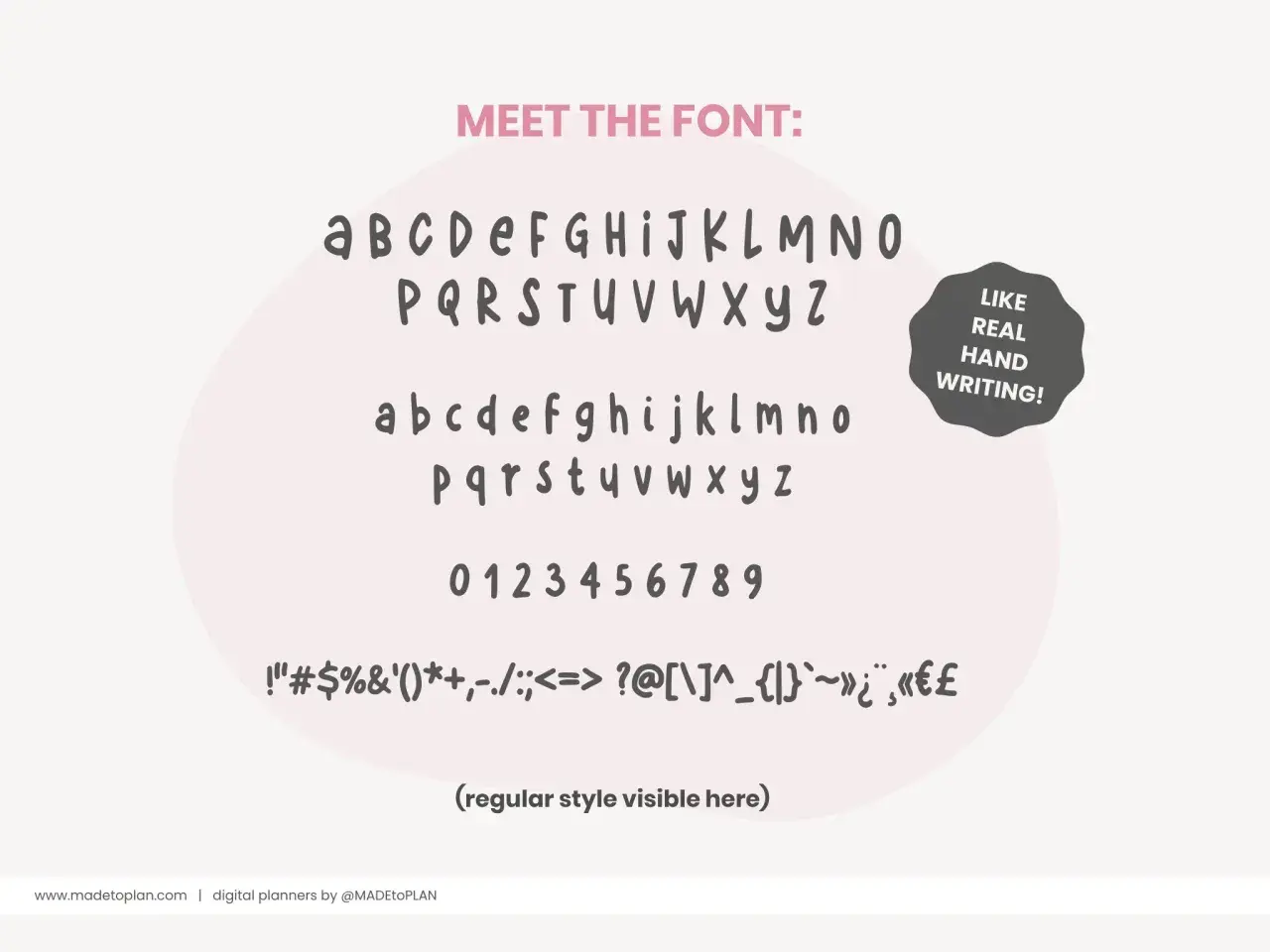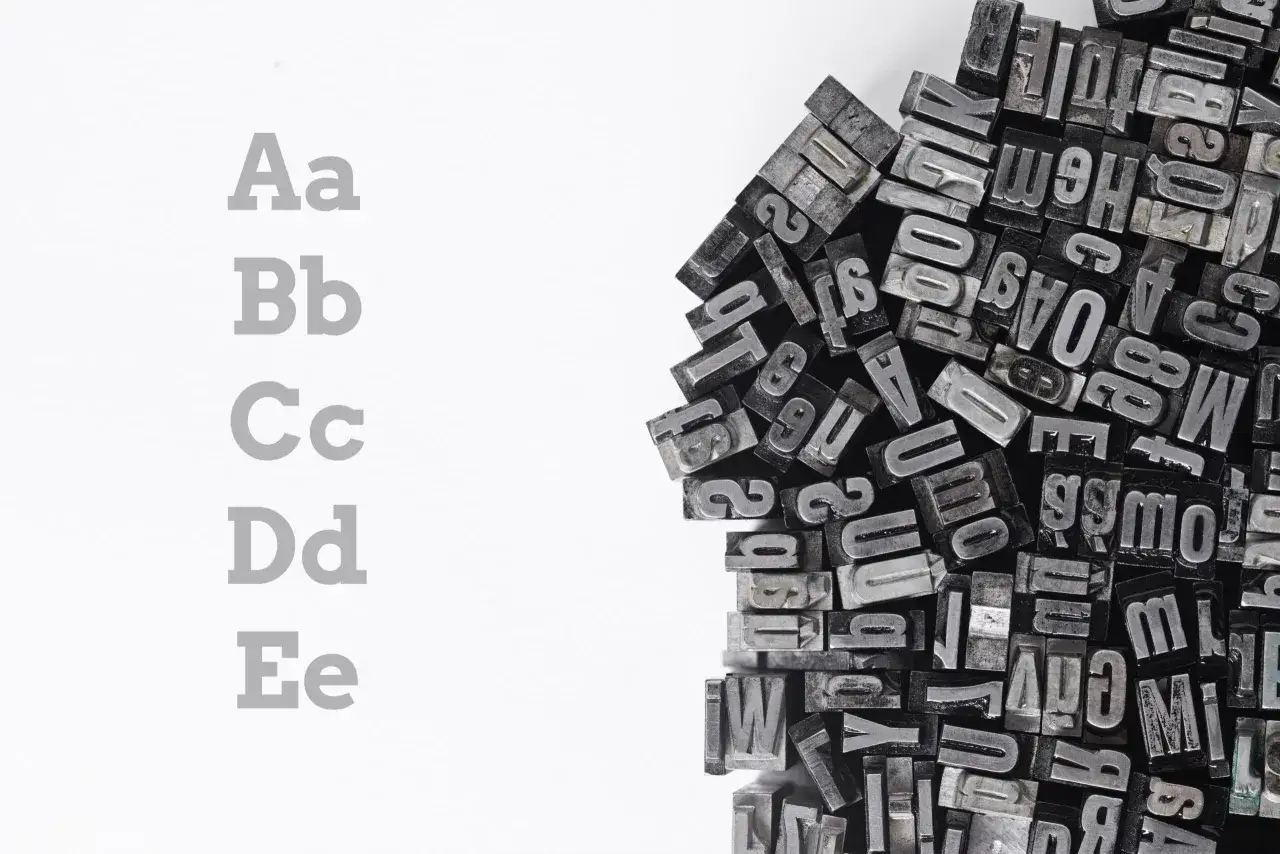
Czcionka, font, krój pisma - Wybierz idealny dla Twojej strony!
Przedstawienie czcionki co to jest, z literami, cyframi i symbolami. Wygląda jak prawdziwe pismo ręczne.
Czcionka to jeden z tych terminów, które brzmią prosto, a w praktyce potrafią mieszać się z fontem i krojem pisma. Poniżej rozkładam to na części: od znaczenia w typografii, przez różnice pojęciowe, aż po to, jak dobrać czytelny zestaw liter na stronie internetowej lub w sklepie online. Dzięki temu łatwiej uniknąć nieporozumień i wybrać rozwiązanie, które dobrze wygląda, szybko się ładuje i nie męczy wzroku.
Najważniejsze rzeczy o czcionkach w skrócie
• Czcionka historycznie oznaczała fizyczny nośnik pojedynczego znaku, a dziś w praktyce często bywa używana zamiennie z fontem.
• W typografii ważniejsze od samej nazwy jest to, czy tekst pozostaje czytelny, spójny i dopasowany do celu strony.
• W internecie font to zwykle plik z zestawem znaków i odmian, który musi ładować się szybko oraz poprawnie obsługiwać polskie znaki.
• Najbezpieczniej wybierać 1-2 rodziny krojów, kilka wag i dbać o odstępy, kontrast oraz wersję mobilną.
• Zły dobór pisma nie tylko psuje estetykę, ale też obniża komfort czytania i skuteczność treści.
Czym jest czcionka w typografii i codziennym użyciu
W klasycznym drukarstwie czcionka była fizycznym elementem używanym do składania tekstu. Jeden znak miał swój materialny odpowiednik, więc litery istniały dosłownie jako metalowe lub drewniane klocki. To właśnie stąd wzięło się pojęcie, które do dziś funkcjonuje w języku potocznym.
W codziennej rozmowie czcionką nazywa się zwykle cały wygląd pisma, czyli to, czy litery są eleganckie, techniczne, nowoczesne albo dekoracyjne. W praktyce projektowej ja patrzę na to szerzej: nie tylko na sam kształt liter, ale też na ich czytelność, odstępy, grubość kresek i zachowanie w różnych rozmiarach. To ważne, bo ten sam zestaw znaków może wyglądać świetnie w nagłówku, a słabo w dłuższym akapicie.
Dlatego przy pracy z tekstem warto pamiętać o prostym rozróżnieniu: historyczna czcionka to rzecz z drukarni, a współczesny wybór na ekranie to już przede wszystkim decyzja typograficzna i technologiczna. Żeby nie mieszać pojęć, od razu rozdzielam trzy terminy, które najczęściej wrzuca się do jednego worka.
Metalowe czcionki, co to za litery? Obok nich Aa, Bb, Cc, Dd, Ee.
Różnica między czcionką, fontem i krojem pisma
Tu najczęściej pojawia się nieporozumienie. Jeśli pracuję nad tekstem na stronie, używam tych słów precyzyjnie, bo każde z nich opisuje trochę inny poziom:
Pojęcie Co oznacza Przykład Kiedy ma sens
Czcionka Historycznie fizyczny nośnik pojedynczego znaku używany w druku Metalowa litera w składzie drukarskim Gdy mówimy o klasycznej poligrafii i historii pisma
Krój pisma Projekt liter i znaków o wspólnych cechach graficznych Times New Roman, Inter, Georgia Gdy opisujemy wygląd i styl pisma
Font Cyfrowa postać kroju pisma, zwykle w konkretnej wadze i odmianie Inter Regular, Inter Bold, Inter Italic Gdy mówimy o pliku lub wersji użytej w systemie
Glif Konkretny rysunek znaku w danym kroju Wersja litery „a” w danym foncie Gdy analizujemy szczegóły kształtu liter i symboli
W praktyce potoczne użycie bywa uproszczone i mało kto w rozmowie codziennej pilnuje tej granicy co do przecinka. W pracy nad stroną, identyfikacją wizualną albo materiałami sprzedażowymi takie rozróżnienie pomaga jednak uniknąć chaosu: łatwiej wtedy dobrać wariant, rozmiar, wagę i zestaw znaków, który faktycznie działa. Gdy to już jasne, można przejść do tego, jak font funkcjonuje w świecie cyfrowym.
Jak font działa w internecie i na urządzeniu
W informatyce font to najczęściej plik z opisem znaków, ich kształtów i odmian. Współczesne fonty są zwykle wektorowe, więc skalują się bez utraty ostrości, a nie jako proste bitmapy. To dlatego ten sam krój może dobrze wyglądać na małym ekranie telefonu i na dużym monitorze, o ile został poprawnie przygotowany.
Na stronach internetowych najczęściej spotykam format WOFF2, bo jest lekki i dobrze wspierany przez nowoczesne przeglądarki. W praktyce warto znać też WOFF oraz formaty OTF i TTF, które częściej pojawiają się przy projektowaniu, instalacji lokalnej albo wymianie plików między systemami.
Format Do czego służy Co warto wiedzieć
WOFF2 Najlepszy wybór do internetu Jest lekki, szybki i praktyczny w większości nowych projektów
WOFF Starszy format webowy Przydaje się jako dodatkowa warstwa zgodności
OTF / TTF Projektowanie, instalacja, praca lokalna Wygodne, ale do strony często cięższe niż WOFF2
W projektach webowych liczy się nie tylko sam wygląd, ale też sposób dostarczenia pliku. Jeśli font ładuje się zbyt wolno, użytkownik przez chwilę widzi zamiennik albo pusty fragment tekstu, a to psuje pierwsze wrażenie. Dlatego w praktyce ustawiam font-display: swap, testuję fonty zastępcze i sprawdzam, czy plik dobrze obsługuje polskie znaki oraz różne grubości. Jeśli ten etap jest dopięty, łatwiej przejść do wyboru pisma pod konkretny rodzaj treści.